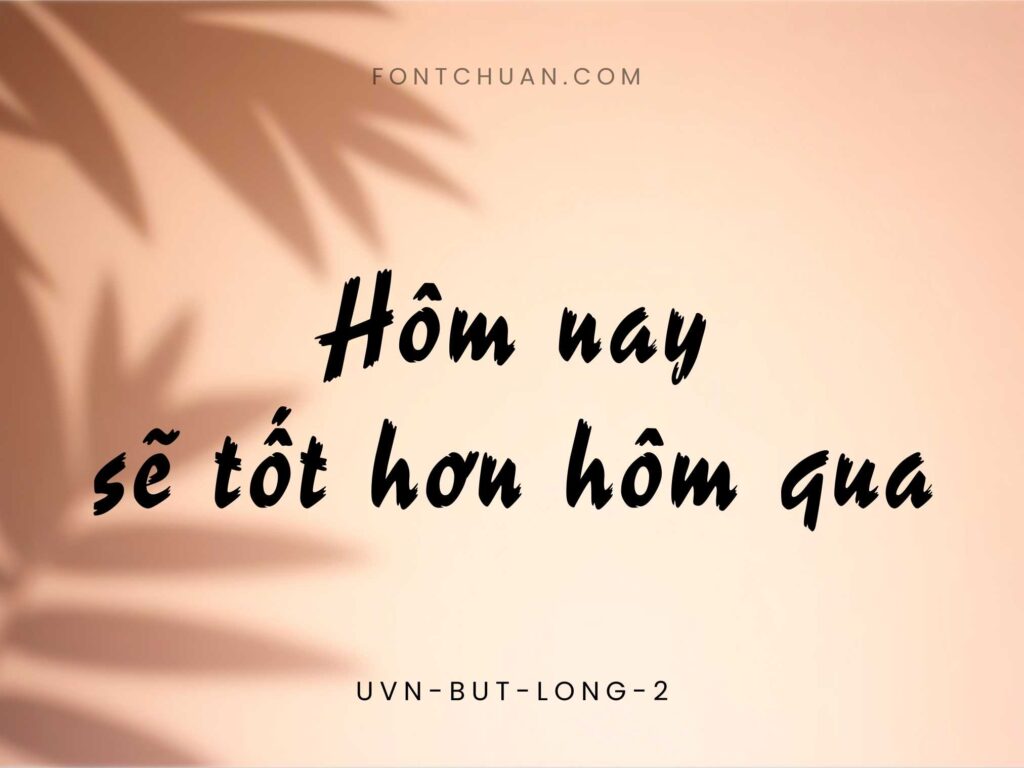
Font UVN But Long 2 Việt Hóa
UVN Bút Lông 2 là một phông chữ thư pháp mang đậm phong cách nghệ thuật viết tay truyền thống. Được thiết kế với các nét bút lông mềm mại và uyển chuyển, phông chữ này tạo nên sự thanh thoát và tinh tế cho các tác phẩm thiết kế. UVN Bút Lông 2 hỗ trợ đầy đủ các ký tự tiếng Việt, giúp người dùng dễ dàng sử dụng trong các dự án sáng tạo liên quan đến văn hóa Việt Nam.
Với thiết kế độc đáo và nghệ thuật, UVN Bút Lông 2 phù hợp cho các ứng dụng như thiệp mời, tiêu đề sách, thiết kế logo và các ấn phẩm nghệ thuật. Trong lĩnh vực sự kiện, phông chữ này có thể được sử dụng trong các dịp như lễ hội, lễ cưới và các sự kiện văn hóa. Ngoài ra, UVN Bút Lông 2 còn là một Font chữ ảnh cưới lý tưởng, giúp tạo điểm nhấn tinh tế cho các thiệp cưới, album ảnh và các sản phẩm kỷ niệm, mang đến không khí lãng mạn, trang nhã và nghệ thuật cho các thiết kế. Font này cũng thích hợp cho các ngành nghề như thiết kế đồ họa, nghệ thuật trang trí và xuất bản.